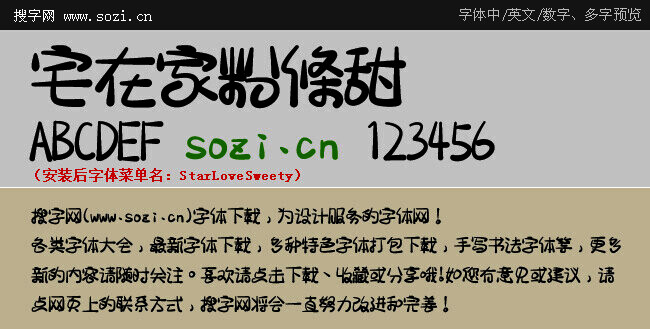
宅在家粉條甜
搜字網(wǎng)給大家提供一款余宅在家粉條甜中文字體下載,宅在家粉條甜是一個(gè)來(lái)自臺(tái)灣省的網(wǎng)友“天天宅在家”創(chuàng)作而成的卡通字體。該字體生動(dòng)活潑,圓滑Q彈,小巧可愛(ài),看上去別有一番趣味。字體適合廣告設(shè)計(jì)、海報(bào)設(shè)計(jì)、包裝設(shè)計(jì)等應(yīng)用。